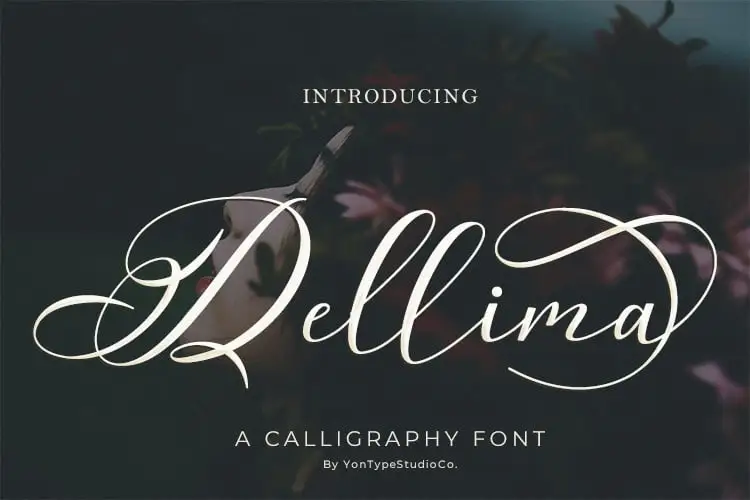
Dellima Calligraphy Font – Download Grátis
Introduzimos a Dellima Calligraphy Font, uma deliciosa escrita que se destina a designers buscando elegância e estilo para seus projetos. Especificamente projetada para os recados de casamento, cartas românticas e marca personalizada feminino. Sua forma suave e delicada oferece um toque de romantismo que pode fazer qualquer projeto brilhar ainda mais. Perfect para quem quer dar um toque especial a seus designs, seja em papelaria de casamento ou até mesmo em branding feminino, a Dellima Calligraphy Font é uma opção perfeita.